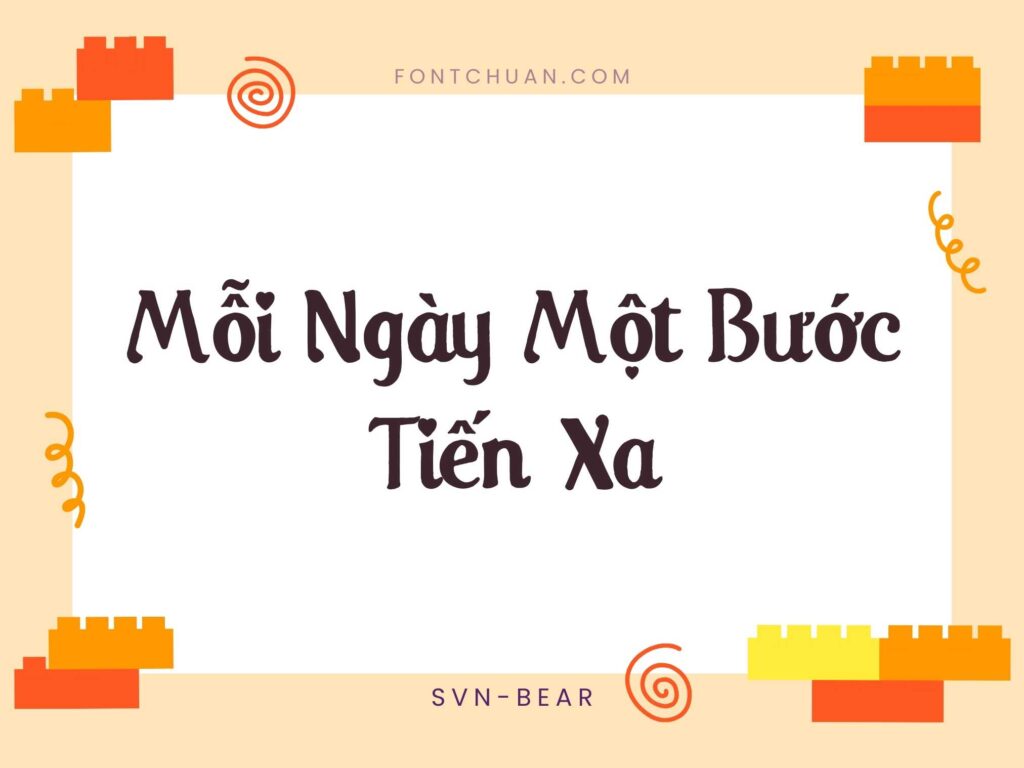
Font SVN Bear Việt Hóa
Bear là một font chữ viết tay độc đáo, mang phong cách mạnh mẽ và năng động. Font này thuộc thể loại Calligraphy, Handwritten và Script, phù hợp cho nhiều mục đích sử dụng như thiết kế logo, tiêu đề, nhãn mác và các dự án sáng tạo khác. Với thiết kế độc đáo, Bear tạo nên sự thu hút và ấn tượng cho các tác phẩm thiết kế. Font đã được Việt hóa để hỗ trợ tiếng Việt bởi Styleno.1 Fonts, đồng thời hỗ trợ nhiều ngôn ngữ khác, giúp mở rộng phạm vi sử dụng trên toàn cầu. Font này được thành viên của Font Chuẩn sưu tầm và chia sẻ, đáp ứng nhu cầu của bạn đọc và ứng dụng thực tế vào các dự án thiết kế.
Đặc điểm thiết kế của Bear bao gồm các đường nét viết tay mạnh mẽ, tạo cảm giác năng động và cá tính. Font này phù hợp cho các ứng dụng như thiết kế logo, tiêu đề, nhãn mác và các dự án sáng tạo khác. Các ngành nghề phù hợp bao gồm quảng cáo, nghệ thuật và thiết kế đồ họa.